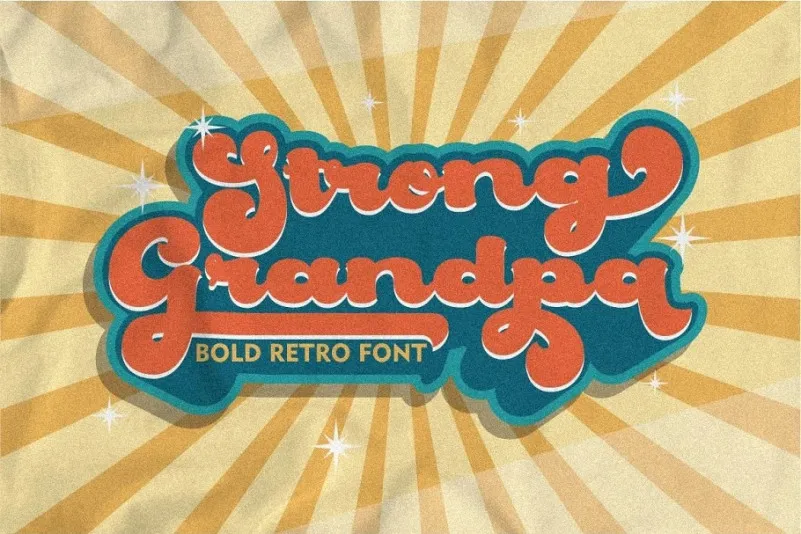
Strong Grandpa Font – Fonte Grátis
Strong Grandpa Font
A Strong Grandpa Font é uma tipografia de script bold criada por PutraCetol Studio com atraente estética vintage. Inspirada nas tipografias e adesivos retro dos anos 60 e 70, ela combina elementos modernos com o estilo tradicionalmente bold. É perfeita para projetos que desejam um toque de nostalgia ou uma vibe vintage, seja em t-shirts, selos de logotipo, embalagens, signagens, capas de livros ou qualquer outro uso que precisa de um ar antigo e sofisticado. Esta fonte é ideal para designers buscando incorporar uma atmosfera vintage em suas criações. Com forte personalidade e estilo original, ela se destaca como a escolha perfeita para os mais diversos projetos gráficos contemporâneos que valorizam essa estética nostálgica.